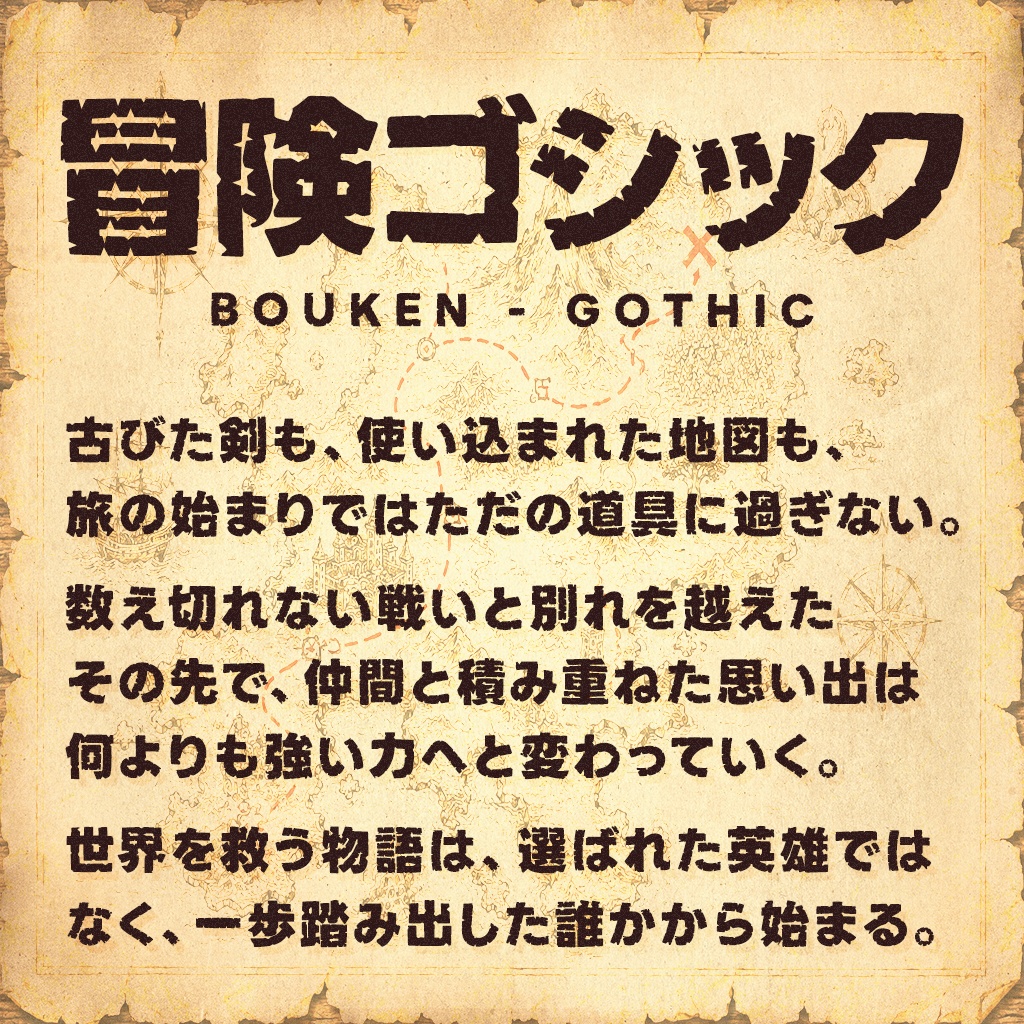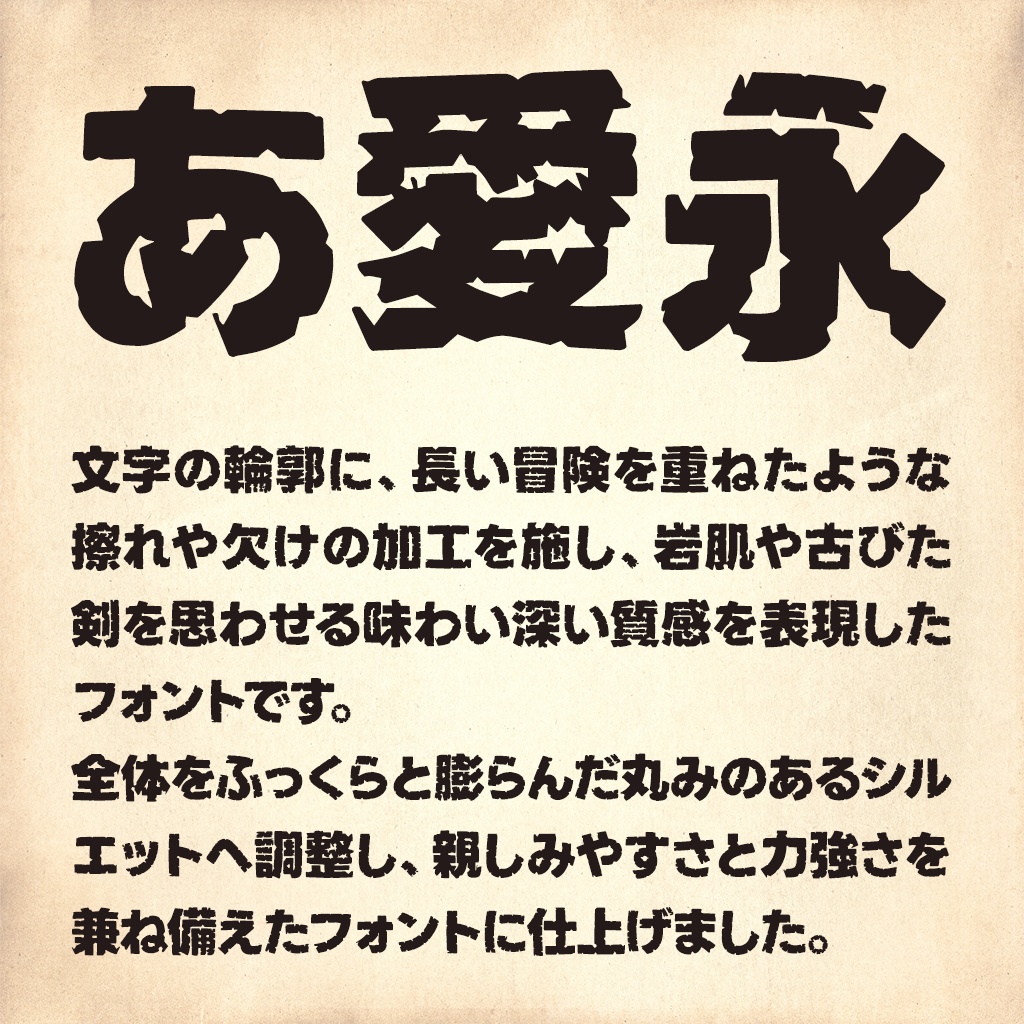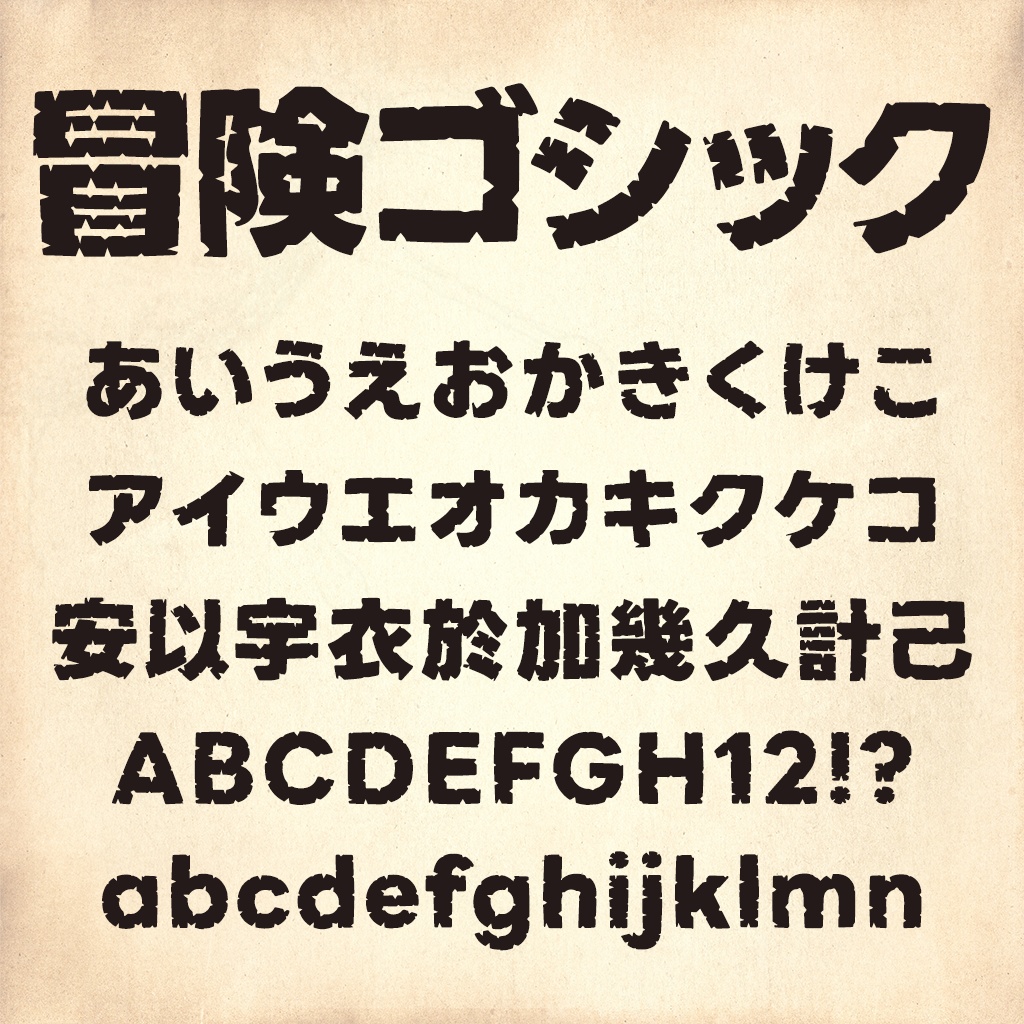
冒険ゴシック
冒険ゴシック(Bouken Gothic)是一款以冒险、奇幻与 RPG 视觉为设计方向的展示字体。字体以 LINE Seed 为基础进行改造,在保留原有字形结构与易读性的基础上,对文字轮廓进行了具有明显风格特征的再设计,通过加入类似长期冒险后留下的磨损、刮痕与缺口效果,让整套字体呈现出一种历经旅途与战斗之后的粗犷质感。
从字体样张来看,冒険ゴシック整体采用较为厚重饱满的字形结构,笔画经过加粗与膨胀处理,使文字拥有非常强烈的视觉重量。与普通粗黑体规整、平滑的边缘不同,这款字体刻意保留了大量不规则的破损细节,文字边缘仿佛经过长时间风吹日晒与不断磨砺,带有一种古老装备、冒险地图以及奇幻世界中的道具所特有的质感。
在字形处理上,冒険ゴシック并没有一味强调硬朗与锋利,而是进一步将整体轮廓调整为圆润、饱满的造型。厚重的笔画与圆润的外形结合之后,让字体在拥有力量感的同时,也具备一定的亲和力。这样的设计既能够表现 RPG、奇幻冒险题材所需要的厚重氛围,也不会让字体显得过于严肃或具有距离感。
冒険ゴシック的风格属性非常突出,因此尤其适合用于奇幻作品、冒险故事、RPG 游戏以及娱乐类视觉设计。无论是游戏标题、游戏実況缩略图、活动 Logo、宣传海报,还是小说封面、角色介绍和主题视觉,都可以利用字体本身粗犷而具有磨损感的轮廓,为画面增加更加鲜明的冒险气息。搭配复古地图、羊皮纸、岩石、木刻等材质背景时,也能够进一步强化字体所营造出的奇幻世界观。
在字符表现方面,字体包含日文假名、中文汉字、英文字母、数字及常用符号等字符,并通过统一的粗厚风格进行设计。英文字母同样具有饱满厚重的视觉效果,与日文及汉字搭配时能够保持较好的整体性,适合用于中日文混排以及游戏、海报等需要突出标题表现力的场景。
需要注意的是,冒険ゴシック属于风格较强的展示类字体,其破损轮廓和粗厚字形更适合标题、Logo、短句等大字号使用。在较小字号或长篇正文中使用时,部分破损细节可能会影响阅读体验,因此更推荐将其作为视觉设计中的重点字体使用。
总体而言,冒険ゴシック是一款将粗犷磨损质感与圆润饱满字形结合起来的冒险主题字体。它没有传统黑体的规整感,而是通过刻意制造的缺口、擦痕与不规则轮廓,让每一个文字都仿佛经历过一段属于自己的冒险旅程。对于 RPG 游戏、奇幻冒险、游戏宣传以及需要营造故事氛围的视觉设计来说,这款字体具有非常鲜明的辨识度和实用价值。